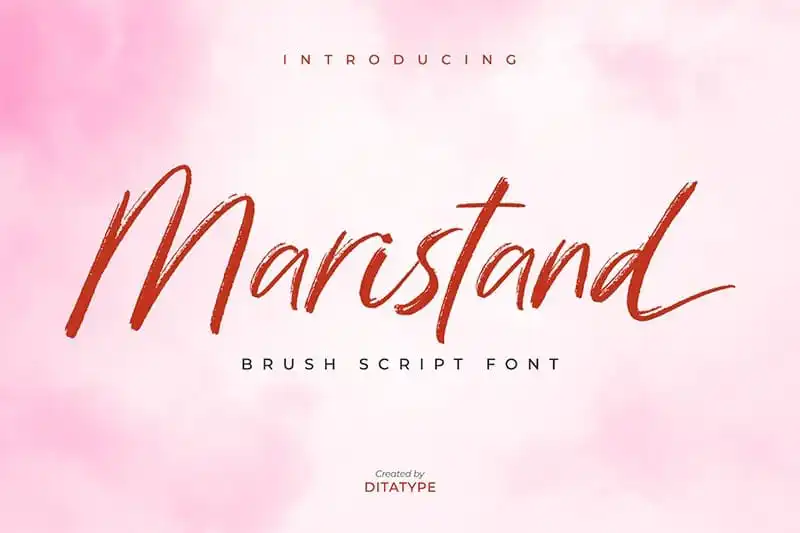
Maristand Brush Font – Download Grátis
Introduzimos a Maristand Brush Font, uma tipografia script que se encontra com traços naturais e desgastados de uma canetinha, e o traço bruto do nosso próprio punho. Esta fonte é elaborada pela Dita type, oferecendo um tipo elegante e atraente. Ela se destina a qualquer projeto profissional de branding. É perfeita para logotipos, branding, casamentos e citações. Esta Maristand Brush Font surge como uma alternativa impecável para aqueles que buscam algo mais fluido e sofisticado em sua tipografia. Com seus traços únicos e suaves, ela captura o jeito de desenhar usando um pincel, dando uma aparência única ao texto. Seja para criações digitais ou impressões físicas, a Maristand Brush Font é uma ótima escolha para qualquer tipo de projeto que exija elegância e sofisticação.